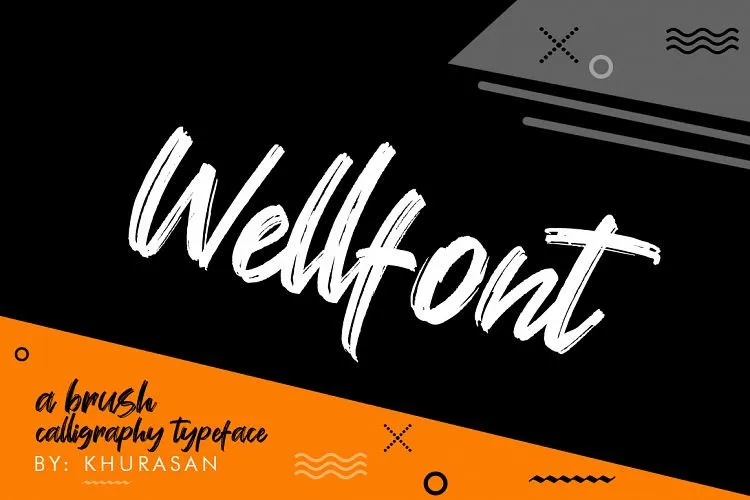
Wellfont Brush Font – Fonte Grátis
Wellfont Brush Font
Através de nossa coleção de fons escuras, apresentamos hoje a YouWellfont Brush Font, uma opção perfeita para quem busca elegância e personalidade em suas criações. Você já conhecia a M.0Type? Bem-vindo ao seu novo projeto criativo! Essa fonte é uma variação do estilo de letras a mão com um toque grunge, tornando-a ideal tanto para projetos artísticos quanto para aqueles que buscam um aspecto casual e descontraído. Wellfont Brush Font oferece uma paleta extensa de caracteres, incluindo todos os tipos de letras maiúsculas e minúsculas, assim como suporte a várias línguas, figuras monetárias, números e pontuação. Desenvolvida pelo designer khurasan, essa fonte traz um ar de elegância vintage às suas criações, tornando-a uma opção versátil para diversos projetos, seja no design editorial ou na composição de sites. Se você procura por uma fonte que combine charme com originalidade, a YouWellfont Brush Font é definitivamente o item perfeito para seu arsenal de ferramentas digitais. Experimentar essa letra a mão grunge traz à sua produção um toque único e moderno, fazendo-a ainda mais irresistível. Não espere! Vá agora e crie algo incrivelmente original com essa fonte versátil e sofisticada.